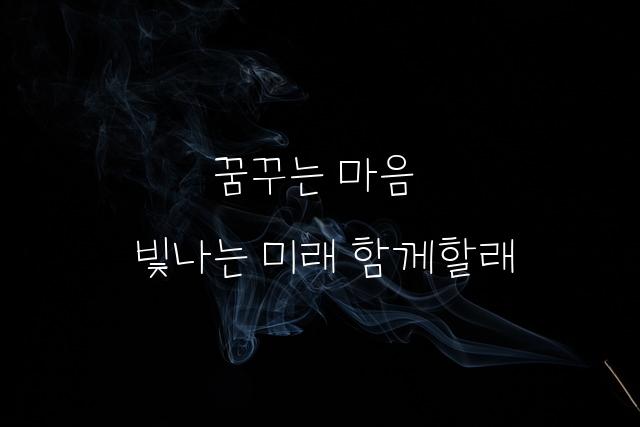
천안꿈누리터 모두체
천안꿈누리터 모두체는 귀엽고 또박또박한 문자가 특징인 폰트로, 가로로 긴 형태와 펜으로 쓴 듯한 느낌이 매력적입니다. 어린이적 감성을 담아 따뜻하고 친근한 디자인을 완성시킵니다.
이 폰트의 인사이트!
친근하고 재미있으며, 어린이와 가족에게 적합한 목소리를 가진 폰트.
천안꿈누리터 모두체은(는) 귀여운 스타일, 두꺼운 스타일, 펜/붓터치 계열의 생김새를 가지고 있으며
교육 자료, 어린이 책, 인사말 카드 등에서 자주 활용되며, 효과적인 메시지 전달에 적합합니다.
이 폰트는 교육, 이벤트/웨딩, 유아/가족 분야에 잘 어울리며,
친근한, 귀여운, 편안한 느낌을 담고 있는 것이 특징입니다.
이 폰트와 유사한 폰트로는 나눔손글씨 펜, 배달의민족 한나체, 해리포터체 등이 있어요. 함께 비교해 보시면 좋습니다!